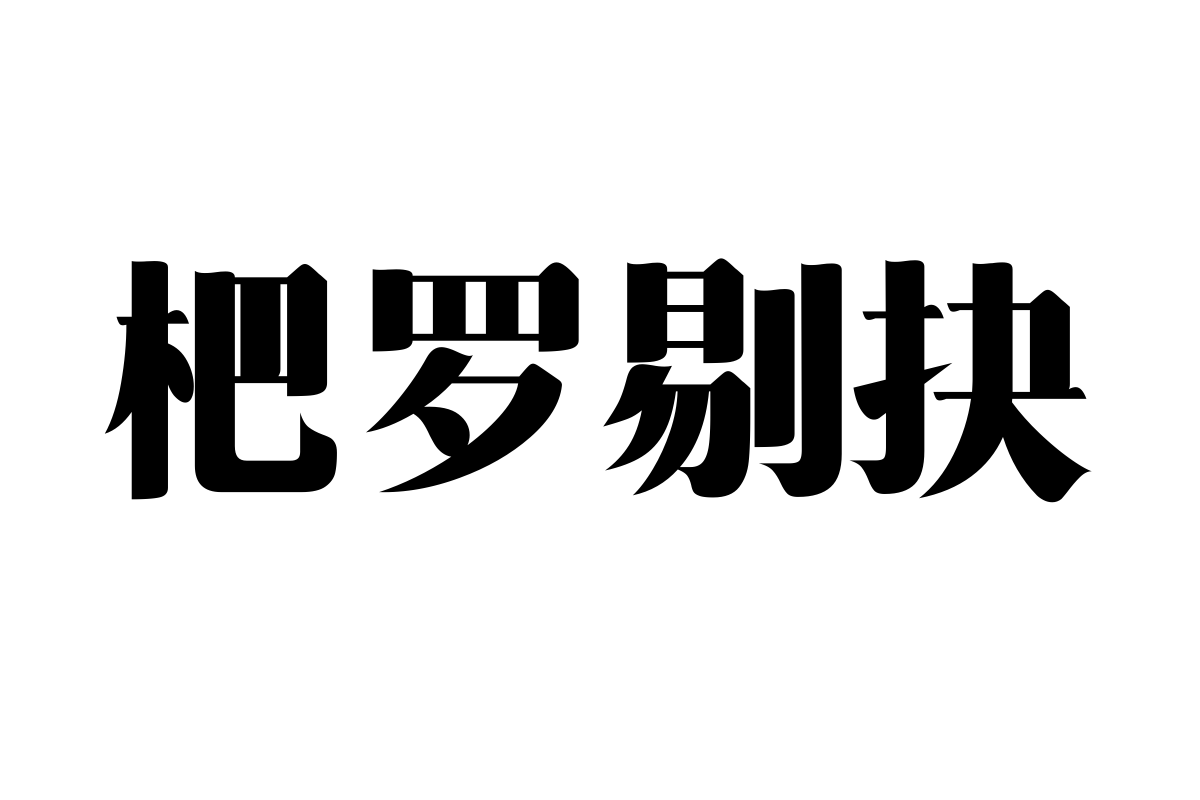
三极粗柔宋简体字体是一款具有独特风格和特点的字体,它由三极公司设计并开发。这款字体采用了传统的书法风格,结合了现代的设计元素,使其既具有传统韵味又不失时尚感。
三极粗柔宋简体字体的特点如下:
1. 字形结构:该字体的字形结构较为复杂,笔画粗细不一,呈现出一种粗犷而有力的美感。同时,字体的线条流畅自然,给人一种优雅的感觉。
2. 笔画风格:在笔画的书写过程中,三极粗柔宋简体字体注重笔锋的变化和力度的控制,使得每个字都显得生动而有力量。这种笔画风格使得字体在视觉上具有较高的辨识度。
3. 字体风格:三极粗柔宋简体字体将传统书法与现代设计相结合,形成了独特的字体风格。它既有古典的韵味,又不失时尚感,适合用于各种商业、文化、艺术等领域的宣传和展示。
4. 适用范围:三极粗柔宋简体字体适用于印刷、电子显示、广告、包装等多种应用场景。无论是在书籍、杂志、报纸还是网页、海报等载体上,都能展现出其独特的魅力。
总之,三极粗柔宋简体字体是一款具有独特风格和特点的字体,它融合了传统书法与现代设计的元素,为设计师提供了更多的创意空间。